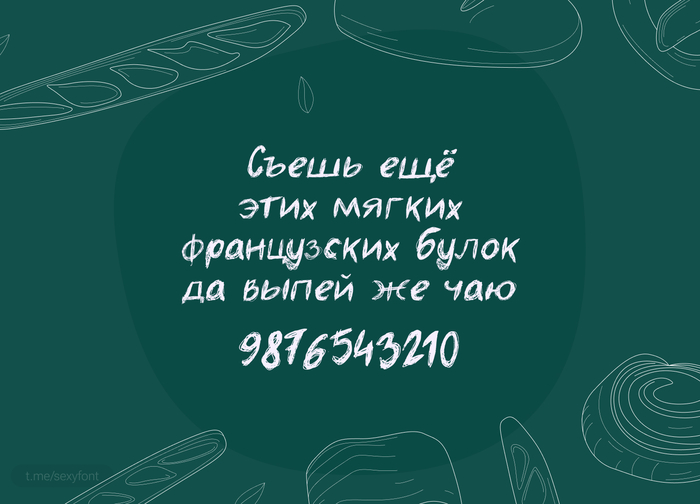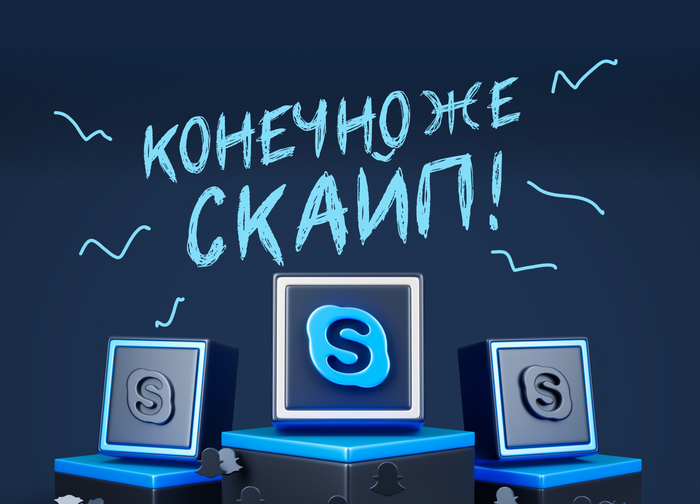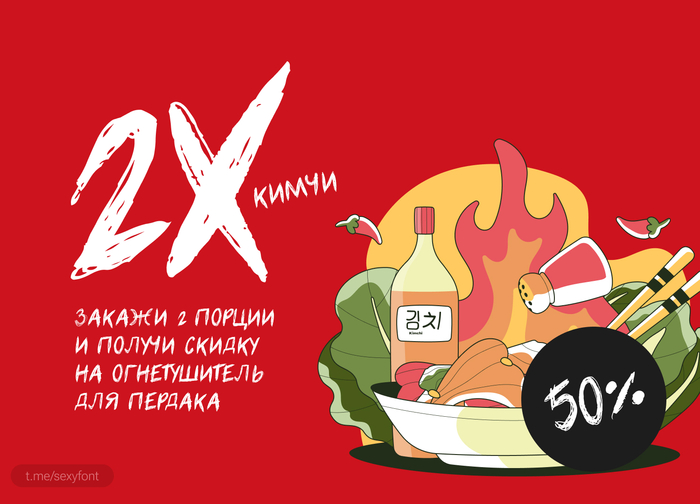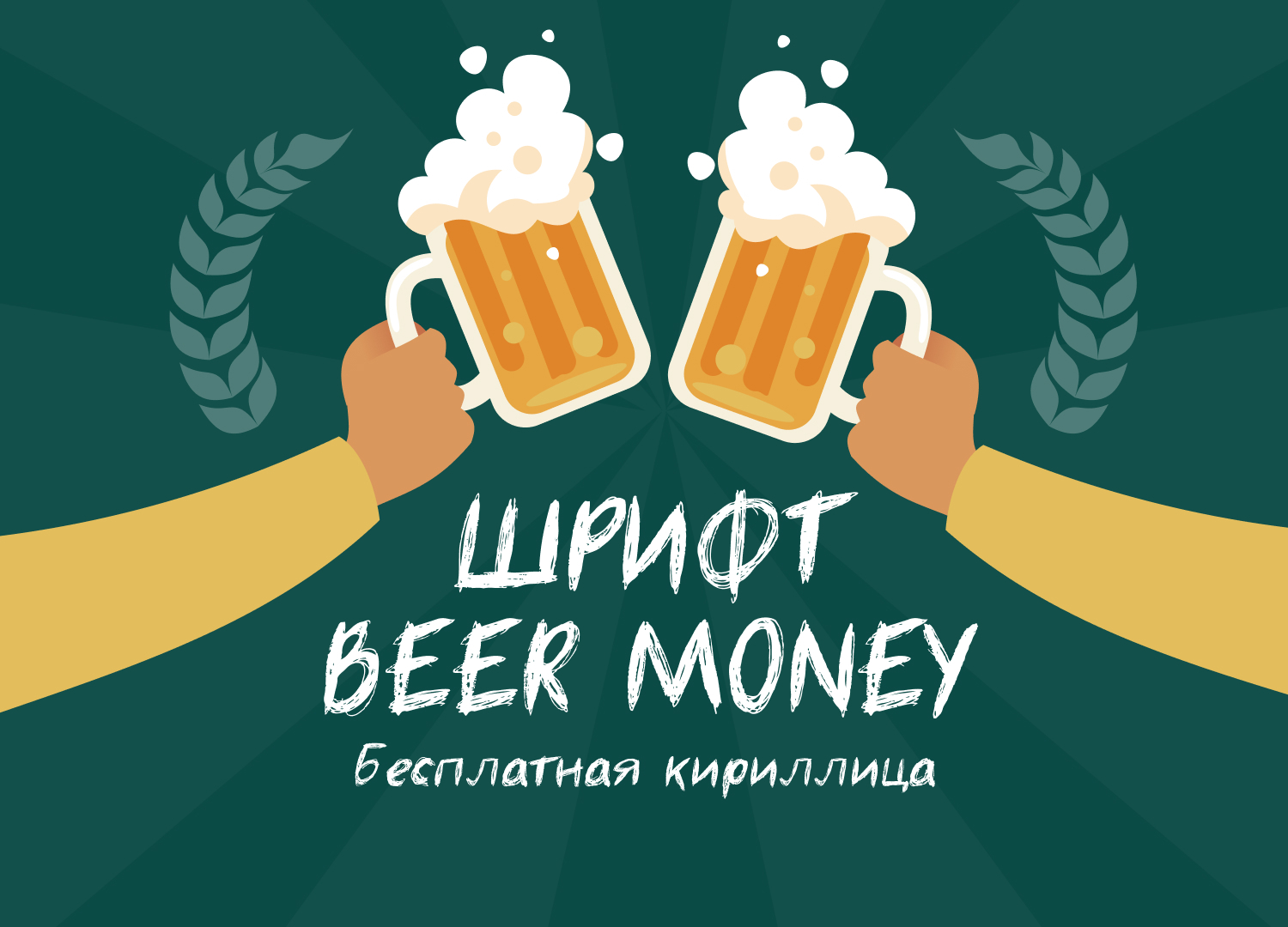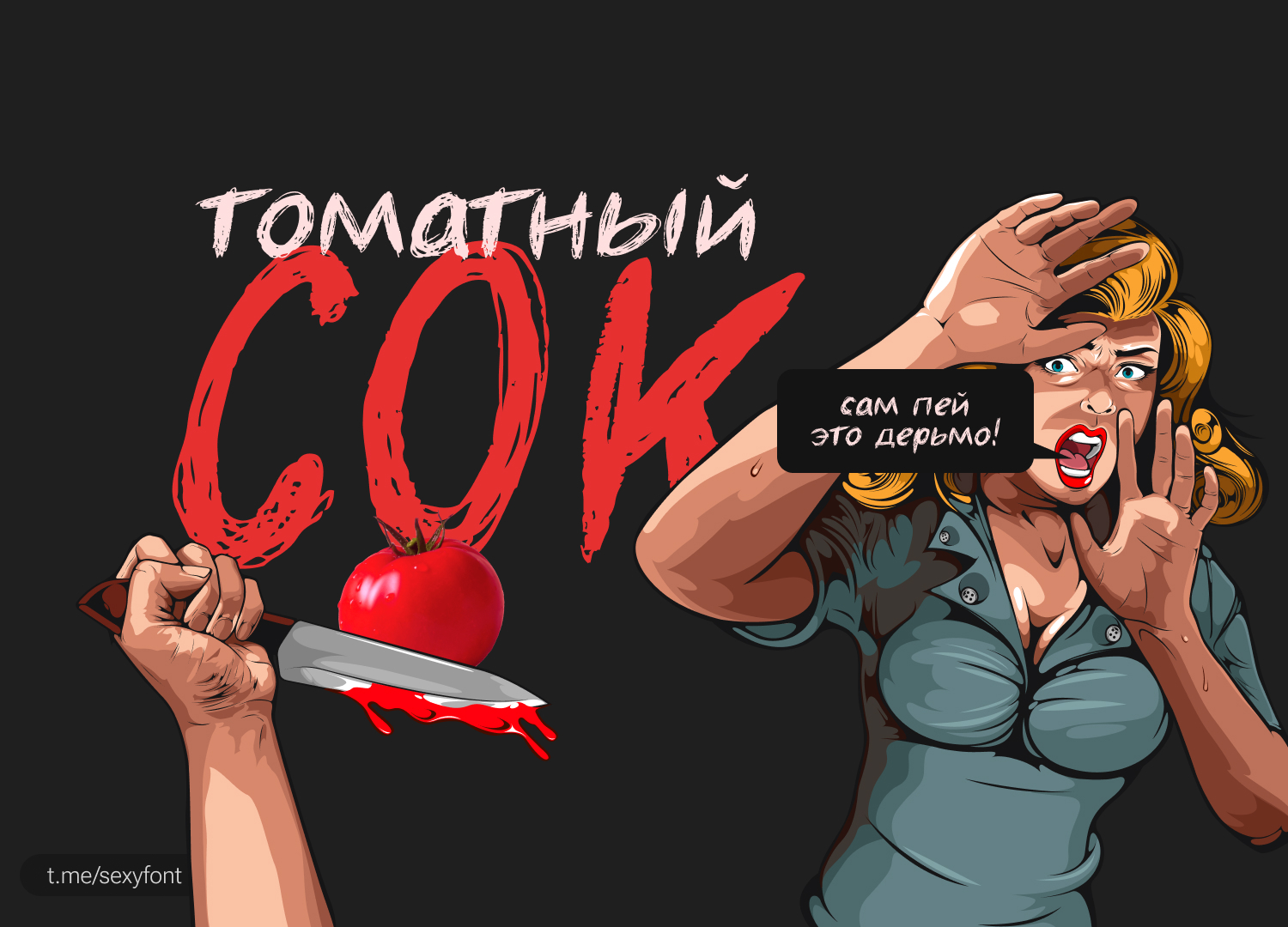
Бесплатный шрифт beer money
Деньги на пиво. Или Beer money. Веселый, рисованный шрифт. По стилю как-будто начеркали фломастером. Даже при таком уровне декоративности вполне читаем в заголовках и небольших абзацах. Но лучше не злоупотре-блеатъ.